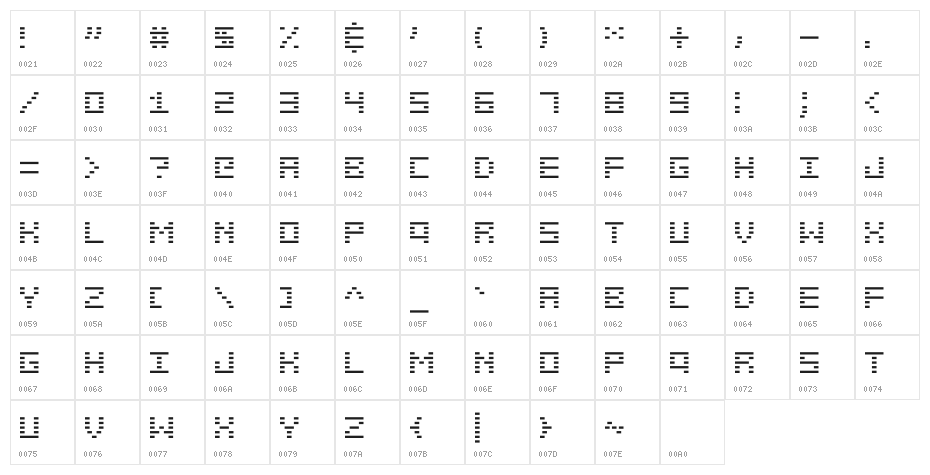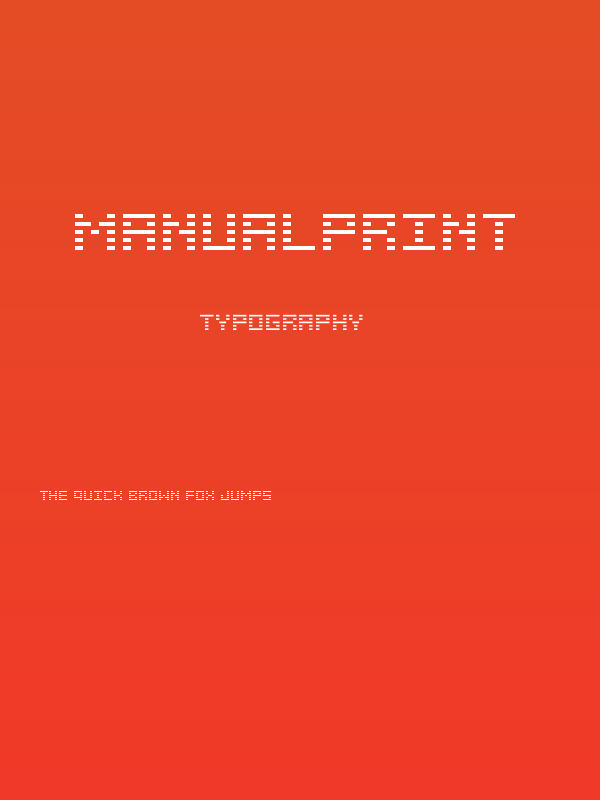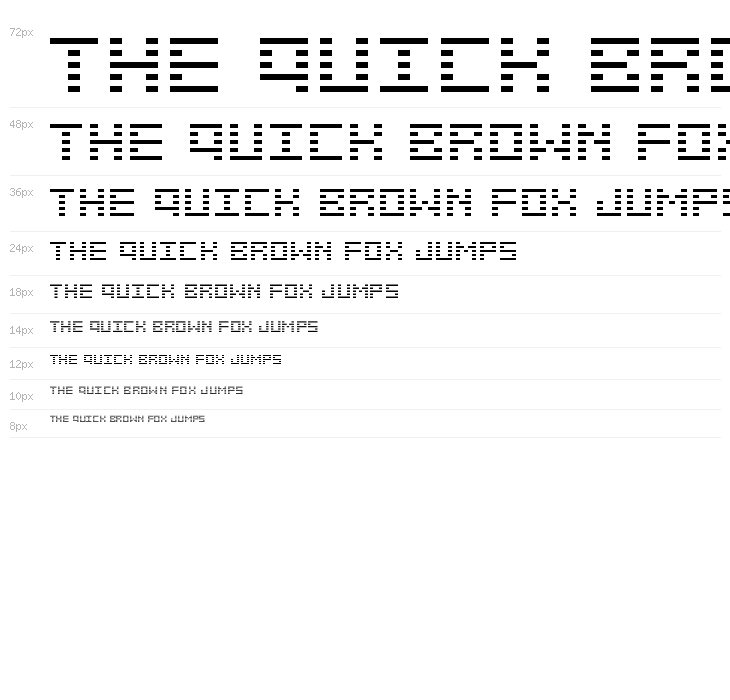
ManualPrint Font
| Stile generale | Retro, Digital |
| Caso d'uso | Headlines, Logos, Digital Displays |
| Progetti proposti | Ideal for digital-themed designs, retro video games, tech-related branding, or any project that requires a vintage digital look. |